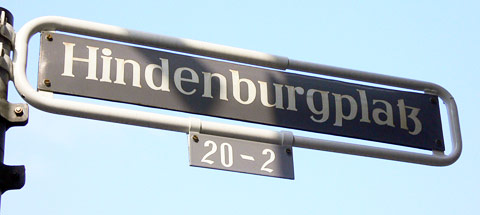
Straßenschildschrift
ich weiß, dass ich Euch zur Zeit etwas strapaziere mit Schriftsuche :roll: ... diesmal suche ich eine Straßenschildschrift. Hat jemand eine Idee, welche Schrift das ist, oder welche in die Nähe kommt?
... ich denke auch nicht, dass die Stadt München für die alten Emailschilder schon einen "Font" verwendet hat :) Das war dann wohl "proprietär".
:-) Aber die sind schon immer wieder schön, diese alten Straßenschilder. Müsste man mal alles digitalisieren. Das hier ist aus Münster. Wie der Punkt auf dem «i» liegt… und die tz-Ligatur erst :biglove:
@Norbert: ... auch nicht unbedingt eine Schrift, in der ich ganze Bücher setzen wollte *hüstel*
@Nina: charmant sind solche Straßenschilder schon :D
@Bertel: hatte ich auch gesehen, danke. "Aktuelle Antiqua" sagt mir nur nichts. :)
Mit "aktuell" ist wohl einfach nur "letztverwendet" gemeint. Scheint wirklich was Proprietäres zu sein ...
Haben die Münchener den Ehrgeiz, eine Schriftmustersammlung zu erstellen? Schön sind die Schilder ja, aber sowas wie Corporate Design wird da nicht gerade sichtbar.
München hat halt Geschichte … :schonklar: